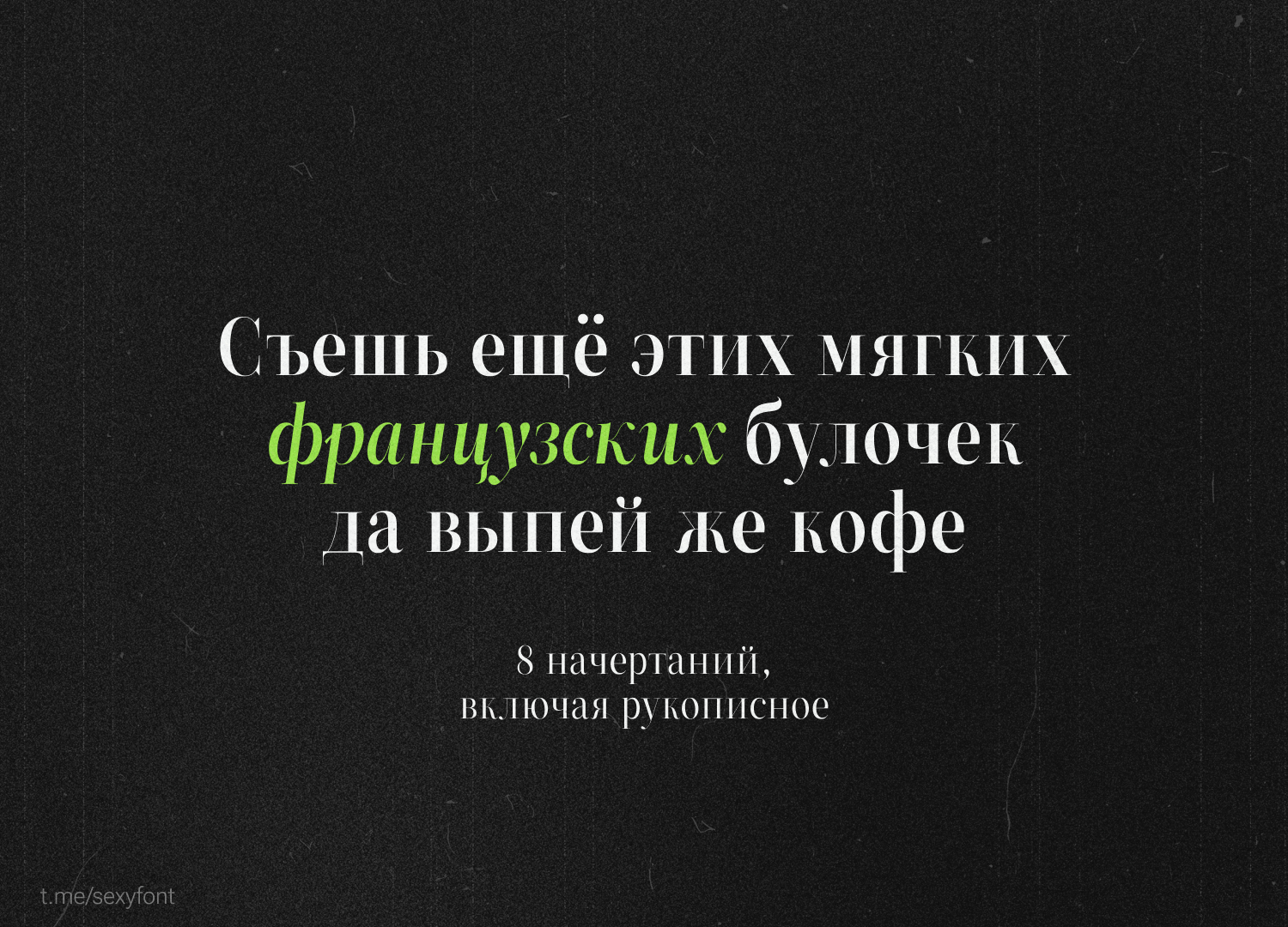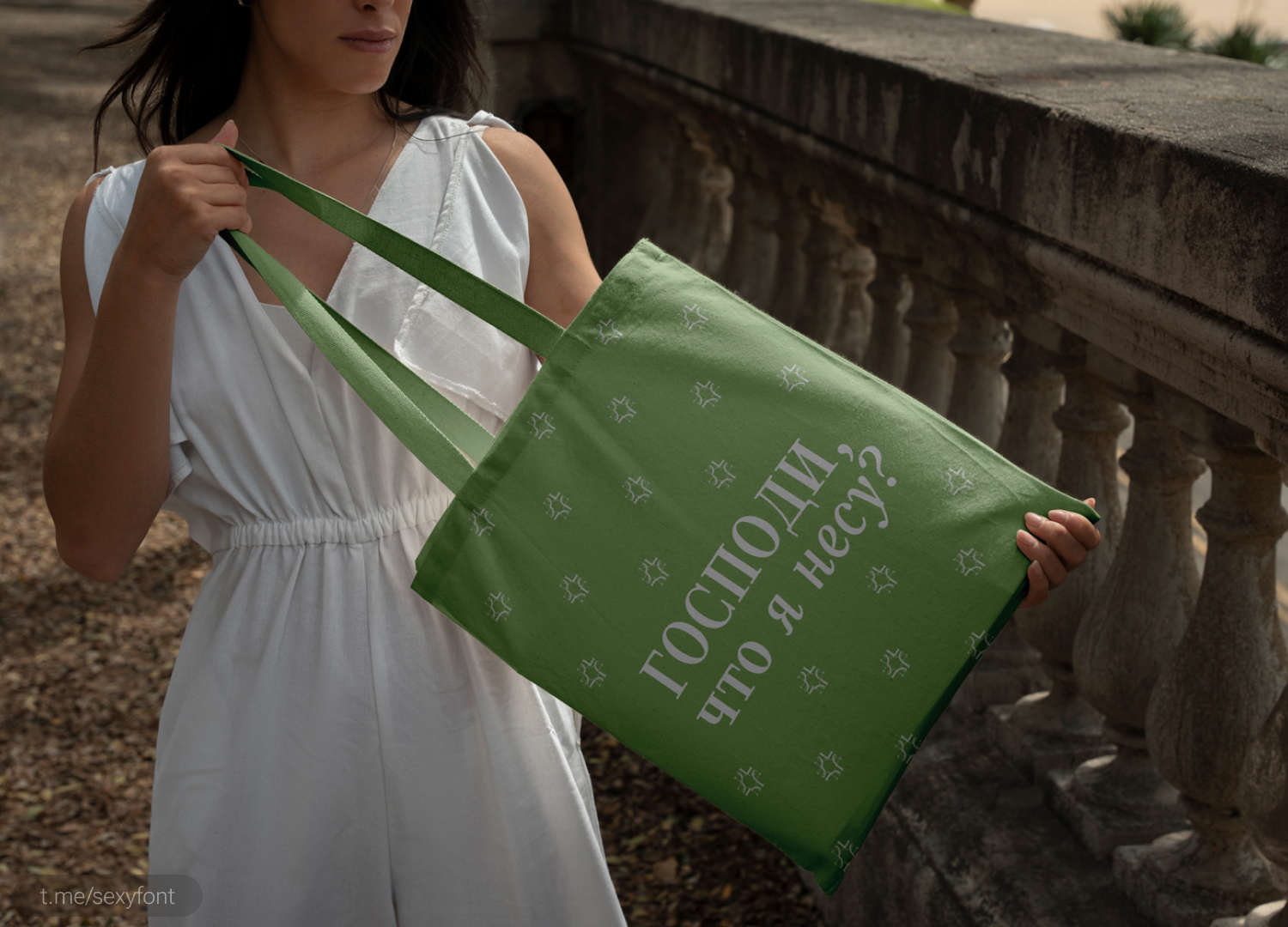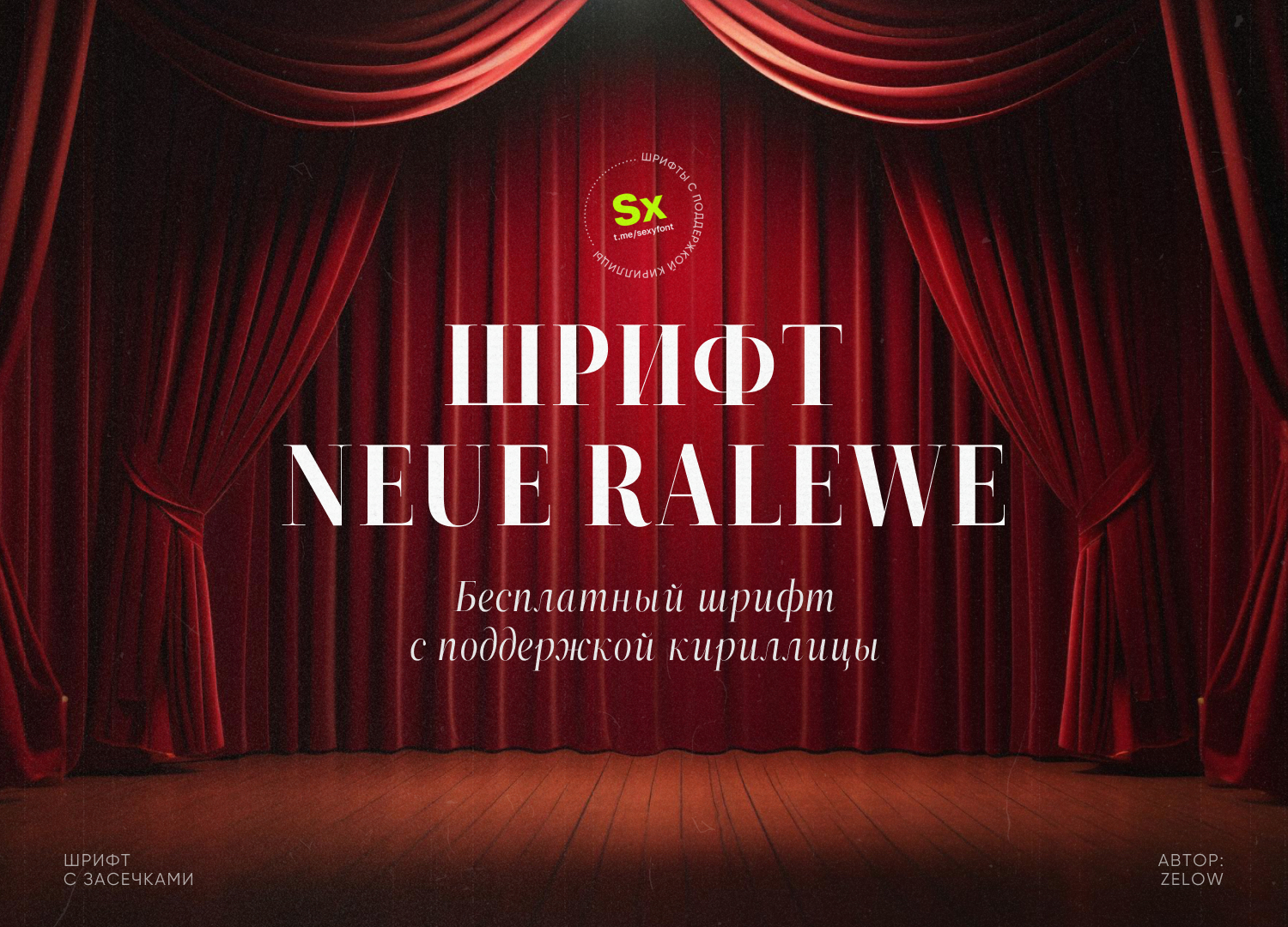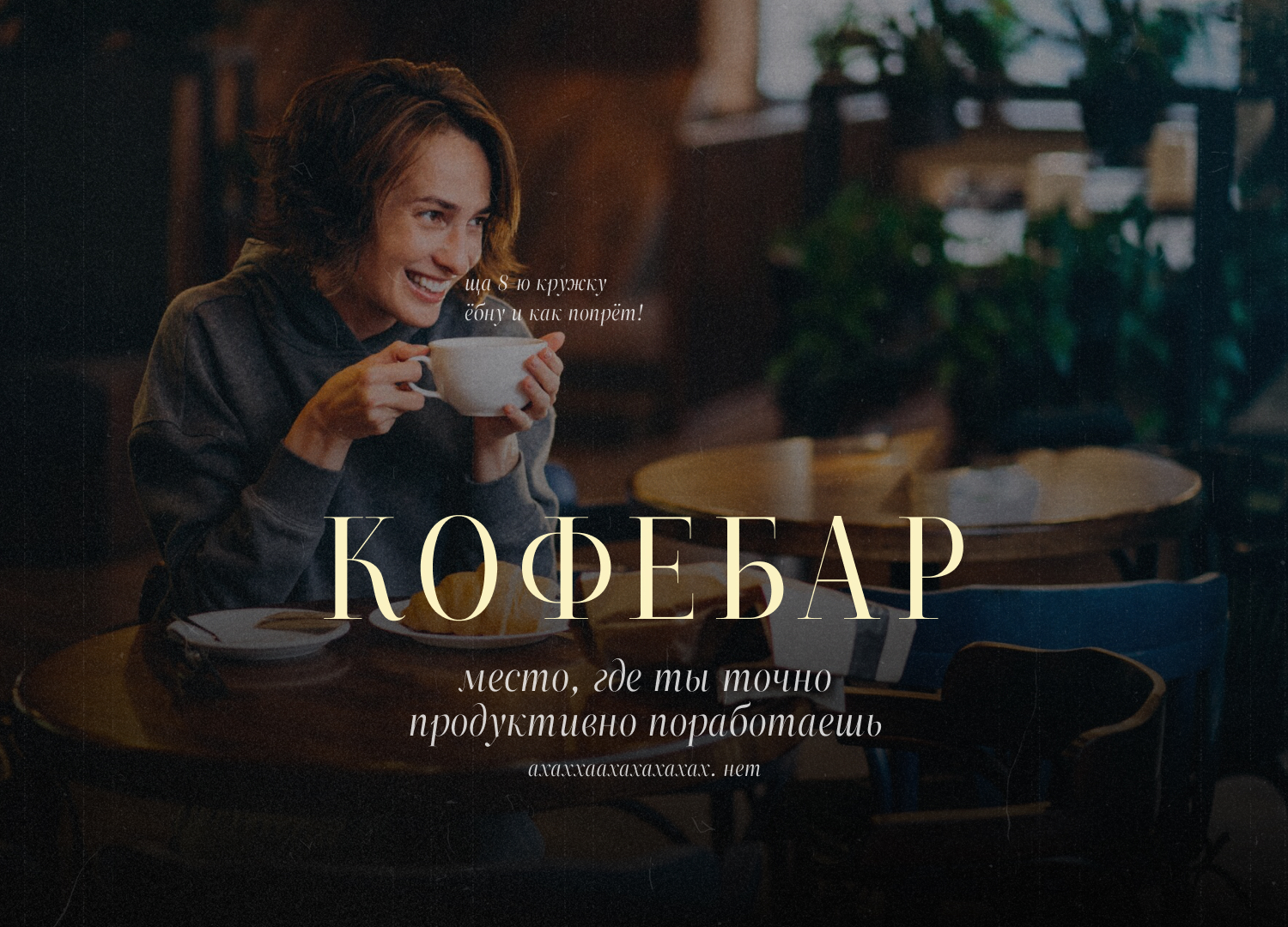
Шрифт ZT Neue Ralewe
Приует! Давненько у нас не пробегало антиквы. Вот, поймал одну. Держи крепче. Шрифт ZT Neue Ralewe и моя фирменная презентация. Есть аж 10 начертаний!